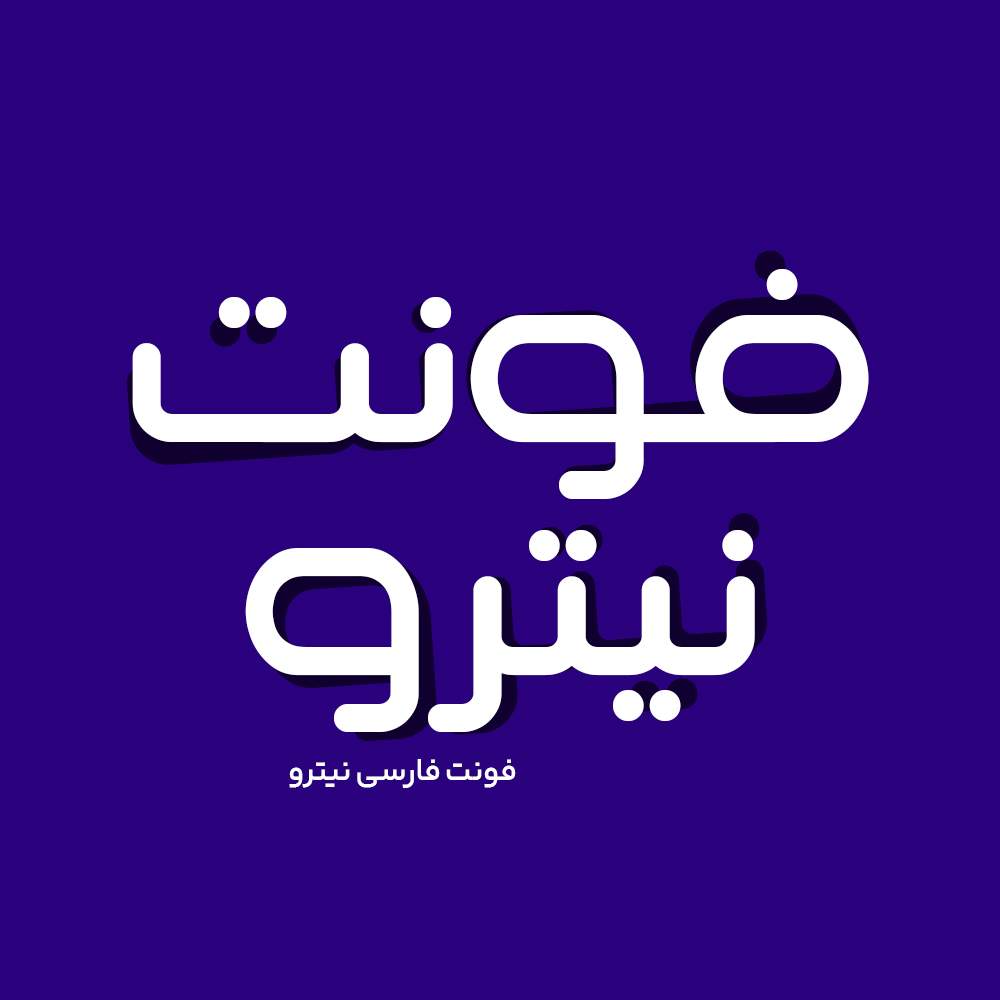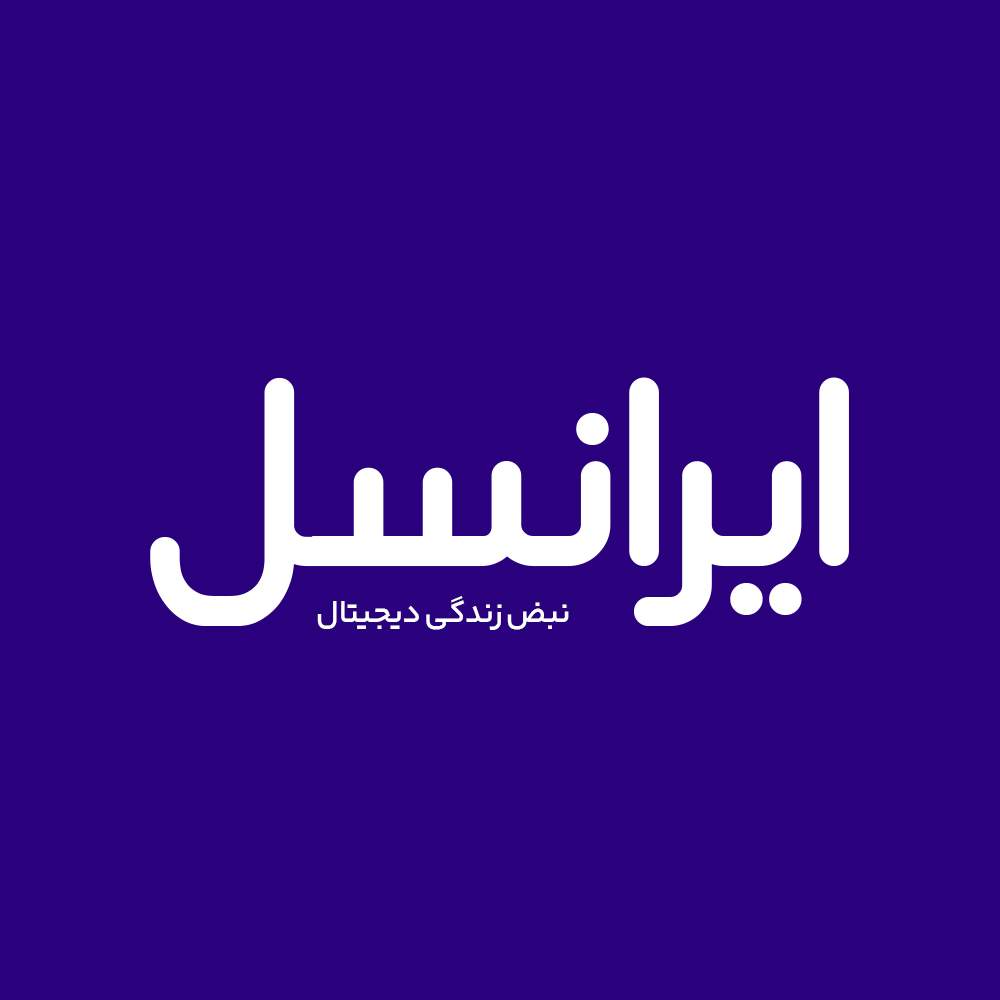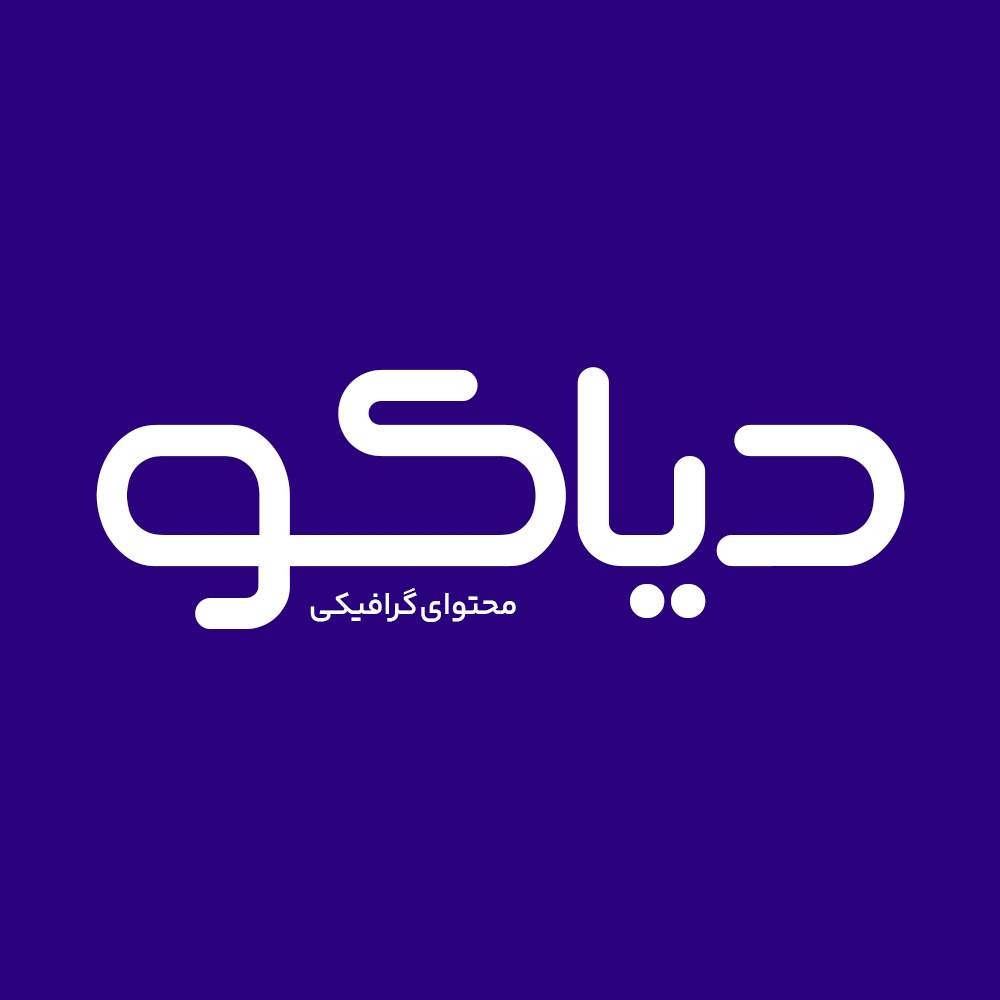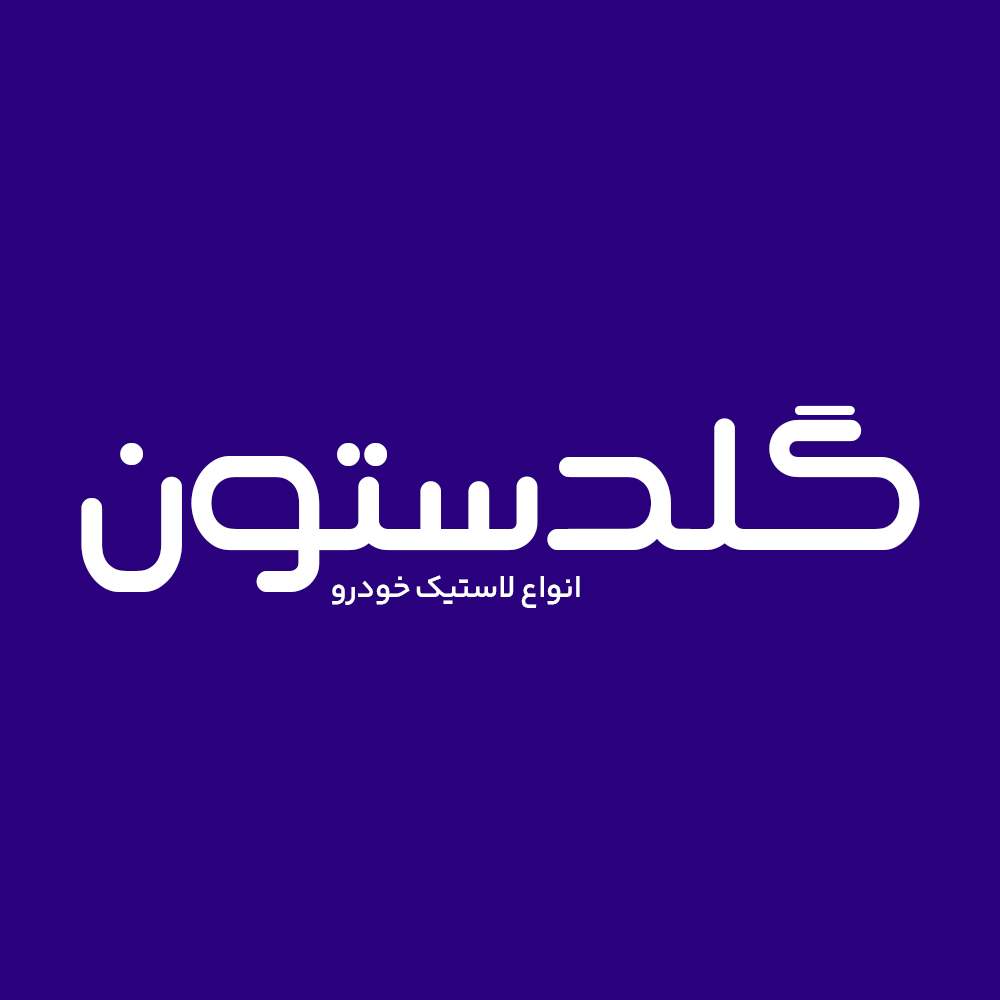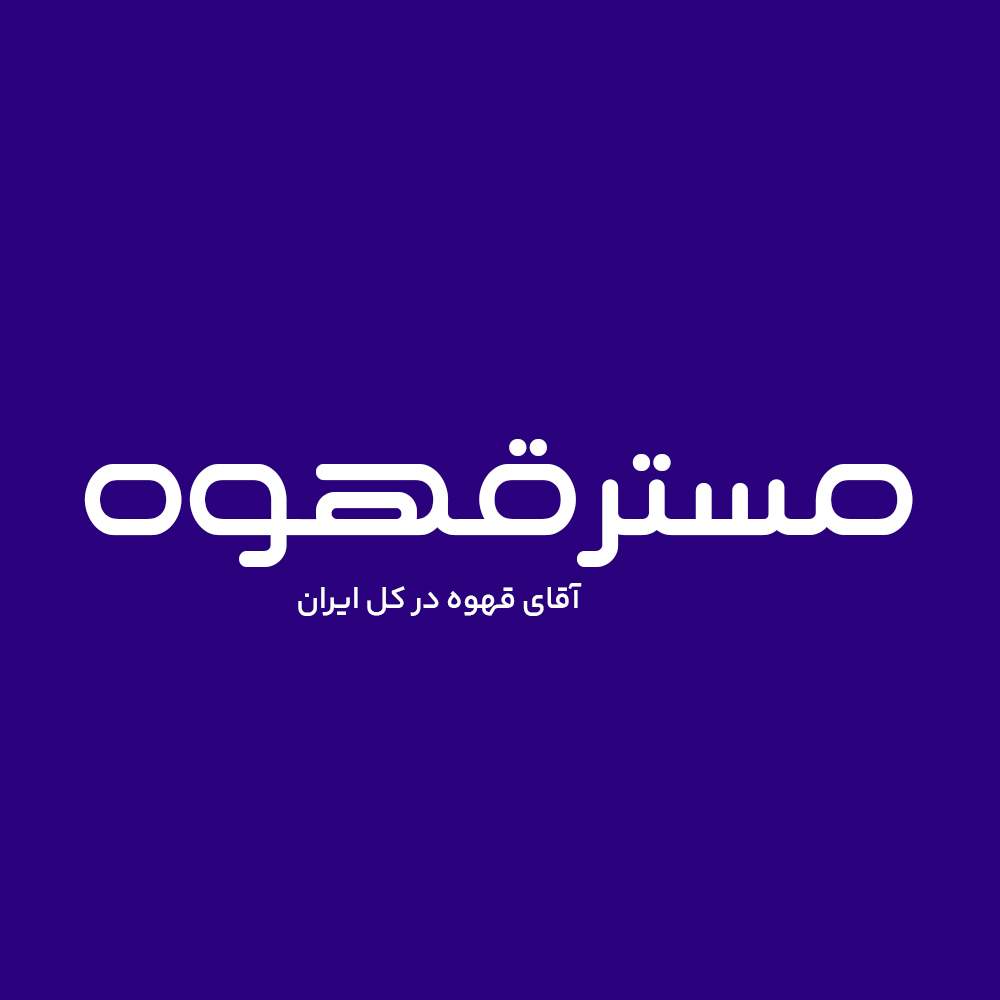
فونت فارسی نیترو Nitro Font
فونت فارسی نیترو از دسته فونت های تایپ و لوگوتایپ، پر انرژی و جذاب است. این فونت با ساختار حروف خود مناسب استفاده در لوگوهای نوشتاری…
فونت فارسی نیترو از دسته فونت های تایپ و لوگوتایپ، پر انرژی و جذاب است. این فونت با ساختار حروف خود مناسب استفاده در لوگوهای نوشتاری می باشد. همچنین از این فونت در طراحی تابلوهای چلنیوم هم به دلیل ساختار منحصر به فردش می توانید استفاده کنید. در ادامه برای شما نمونه تایپ های این محصول حرفه ای رو آماده کردیم که میتونید مشاهده کنید.
پیشنمایش و نمونه تایپ های فونت نیترو
فونت فارسی نیترو Nitro Font